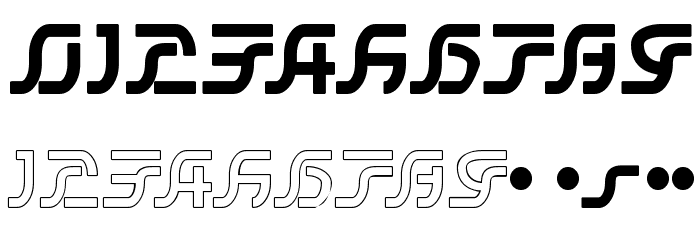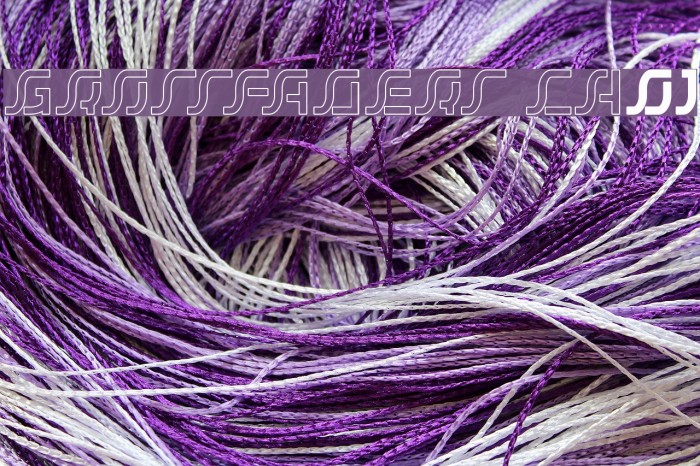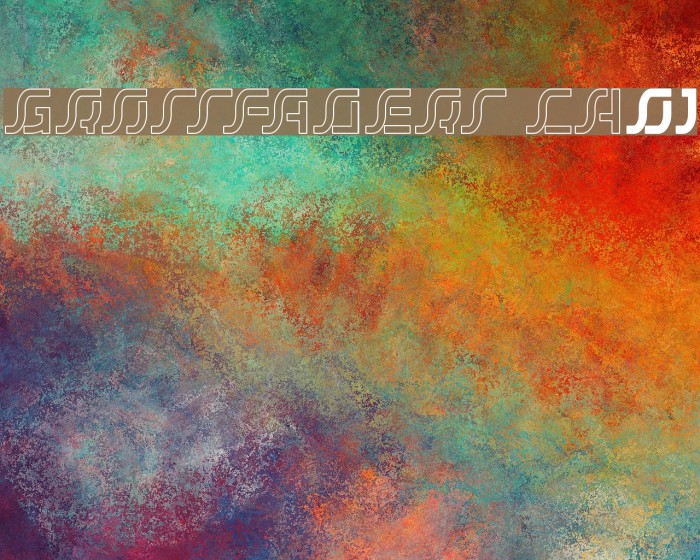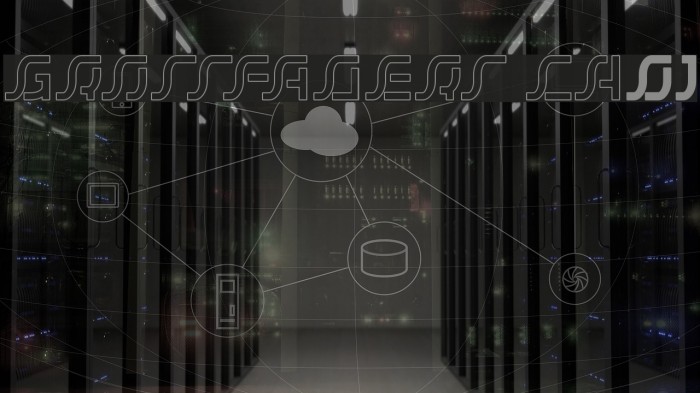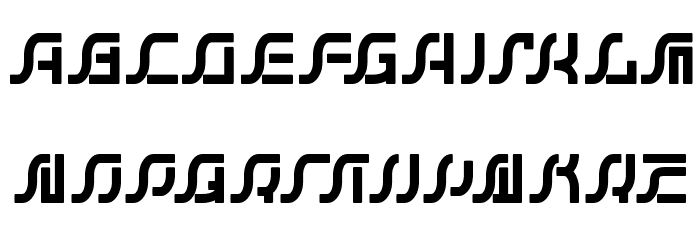
GROSSFADERS CH01 Font
| Caso de uso | Logos, Headlines, Posters |
| Proyectos propuestos | Ideal for sci-fi themed projects, modern branding, digital artwork, and innovative product packaging. |